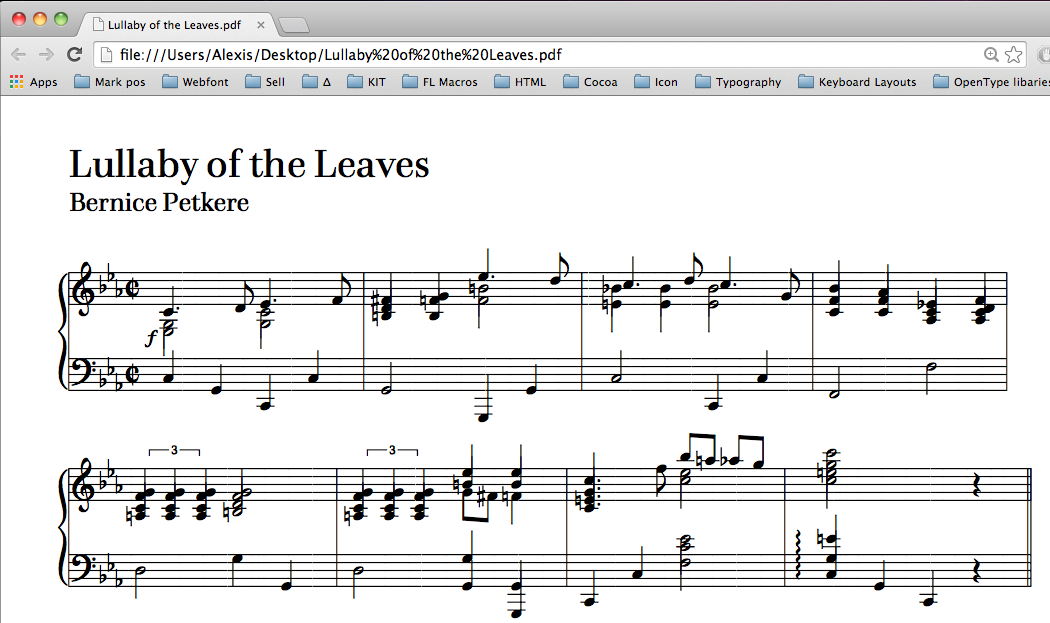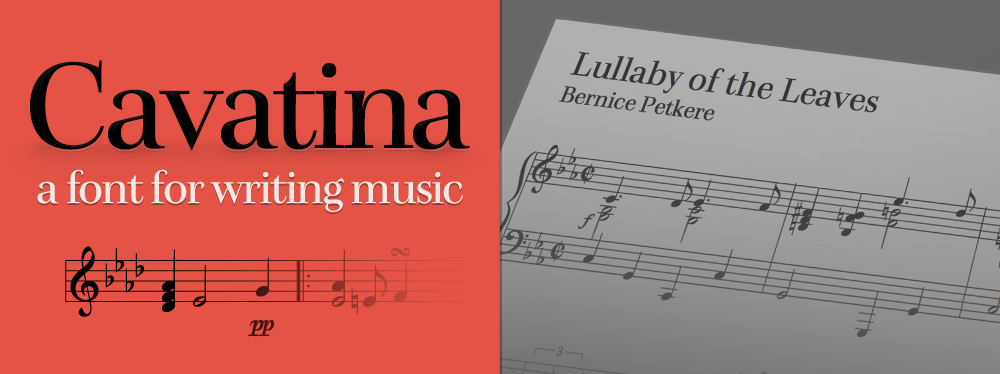
Cavatina — die Schrift für den schnellen Notensatz
Ich präsentiere euch Cavatina: eine Schriftenfamilie für den musikalischen Notensatz. Es handelt sich um eine technische Schrift, die man als solche in einem normalen Texteditor benutzt und die durch OpenType Features den Notensatz automatisch formatiert. Die Idee ist mit dem Ausgangspunkt von Travis Kochel' FF Chartwell verwandt, die OpenType Schriftenarchitektur zu "missbrauchen" und auszuschöpfen. Also: diesmal leider keine Schrift (nicht nur) für Designer, sonder für Musiker, besonders für Hobby-Musiker und Musiklehrer ;-)
Zur Schrift wurde ein Texteditor entwickelt, mit dem man die Kompositionsentwürfe als MIDI abspielen und zudem als MusicXML-Datei übersetzen lassen kann, die man in allen gängigen Notensatzprogrammen öffnen und bearbeiten kann.
Interessantes Projekt, herzlichen Glückwunsch! Da ich gerade in Elaine Goulds "Behind Bars" rumlese, habe ich gedacht, die Cavatina wäre eventuell eine Möglichkeit, die vielen kleinen Notenbeispiele in diesem Buch zu setzen. (Sollte jemand mit dem neuen Standardwerk des Notensatzes nicht vertraut sein: Unter dieser Adresse gibt's ein paar Probeseiten: http://www.behindbarsnotation.co.uk/brochure/blad.pdf ) ;-)
Es ist ja eine elende Arbeit, jedes Notenbeispiel extra in einem Notensatzprogramm zu erstellen und dann z.B. in InDesign weiterzuverarbeiten. Könnte man mit der Cavatina solche Seiten einigermaßen komfortabel in InDesign nachbauen? Ich stelle mir vor, dass dies ein interessanter Anwendungsfall wäre.
Zweite Frage: Bis zu welchem Grad an Komplexität lassen sich denn Notenbeispiele mit der Cavatina generieren? Ich habe als private Übung vor einer Weile Seiten aus Forkels alter Bachbiographie als "moderne" Ausgabe gebaut. Da gibt's z.B. eine Seite mit Notenbeispielen: die Anfänge (jeweils 2 bis 3 Takte) aus Bachs Englischen Suiten; das ist nun kein furchtbar komplizierter Notensatz, im Detail dann aber doch nicht ohne Probleme, wenn's gut aussehen soll. Ließe sich so etwas noch mit der Cavatina erreichen?
Und ich würde gern das Beispiel einer Notenseite sehen, nur um einen Eindruck von der Gestaltung der eigentlichen Notenzeichen zu gewinnen (spontan scheint mir die Anmutung doch recht weit von gängigen Noten-Schriftarten entfernt).
Gerade für Broschüren wie "Behind Bars", die sämtliche Zeichen eines Notensatzes präsentieren sollen, ist Cavatina nicht geeignet, da Cavatina erweiterte Zeichen wie die Strichrichtung-Zeichen bei Saiteninstrumente oder die Tremmolozeichen nicht unterstützt. Jedoch ist Cavatina erst recht für solche Anwendungsfälle gedacht, in welchen kürzere Notensätze und Schriftsatz abwechselnd vorkommen. Leider erlaubt die Schrift nur einfache bis halbkomplexe Notensätze, weshalb Genres wie Jazz nicht in Frage kommen.
Wenn der Notensatz "gut aussehen soll" und Feineinstellungen wichtig sind ist Cavatina nicht die beste Alternative. Cavatina schafft das was sie kann, weil sie auf präzise Feineinstellungen vonseiten des Users verzichtet. Da Cavatina auf Eingabegeschwindigkeit gerichtet ist, gelten solche Layout-Bearbeitungen als Ablenkung. Also kurz: Cavatina ist nicht zum Drucken, sondern zum Schreiben. Ich hoffe das stellt die Dinge klar ;-)
Einen Eindruck, wie der Notensatz mit Cavatina aussieht, kannst du unter folgendem Link bekommen: cavatinafont.com/download-sample (Siehe z.B. dass die einzelnen Zeilen nicht die gleiche Länge haben, was man auch manuell hätte machen können, aber wiederum nicht zum Zweck der Schrift passt.)
Vielen Dank für den Link und die Erläuterungen. Schade, dass die Schrift für "ambitioniertere" Drucksachen nicht geeignet ist; aber vielleicht gibt es andere Anwendungsbereiche, wo es auf die Kombination von Text und Notenbeispielen ankommt (Arbeitsblätter für Musiklehrer z.B.). Ich stelle mir jedenfalls vor, dass hier ein wirkliches Interesse an einer fontbasierten Notensatzlösung bestehen könnte.
Als Kompositionstool kann ich mir das Ganze noch nicht recht vorstellen. Für die einen ist's zu viel (der Hobbymusiker, der nur ein paar Zeilen aufschreiben möchte und das einfach mit Bleistift und Papier erledigt, bevor er ein Eingabesystem erlernt), für die anderen zu wenig (sobald die musikalischen Ideen ein bisschen komplizierter werden).
Eine kurze Frage zur verlinkten PDF: Ist es Zufall, dass in dem Beispiel einige Formen "kaputt" sind? Viele Notenlinien sind unterschiedlich dick und teilweise unterbrochen; der Violinschlüssel ist, aus der Nähe betrachtet, an unpassenden Stellen geknickt; das gilt auch für die "Punzen" einiger halber Noten. (Die geknickten Balken bei einigen Triolen finde ich nun wieder interessant; das erinnert mich an barocke Musikhandschriften mit ihren elegant gekrümmten Notenbalken ...)
Zur zweiten Frage: Bei der unterschiedlichen Strichbreite von Notenlinien ist mit Sicherheit der PDF-Reader daran schuld. Versuch's, mit einem anderen Reader zu öffnen. So sieht's beispielsweise bei mir in Chrome aus:
Den Violinschlüssel habe ich mit Absicht so gezeichnet (und vielleicht hat bei dir der PDF-Reader den noch weiter "kaputt" gemacht). Die Notenschlüssel, die Taktnummern und die Dynamik haben alle den selben Stil, als wären sie mit einem Pinselstift gezeichnet worden.